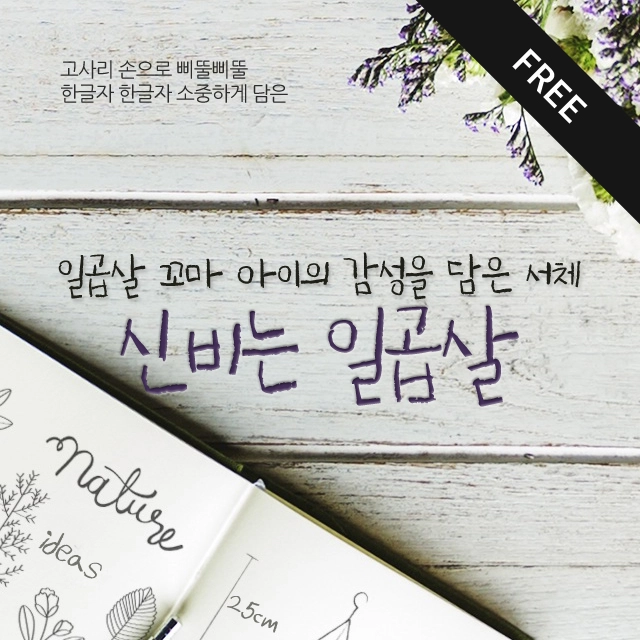
신비는 일곱살
삐뚤삐뚤 못 생겼지만, 일곱살 꼬마의 순진무구한 감성이 폴폴 풍기는 사랑스러운 폰트, 신비는 일곱살
한글 2,350자 / 영문 52자 / 약물 50자
신비는 일곱살 Regular 1종
삐뚤삐뚤 못 생겼지만, 일곱살 꼬마의 순진무구한 감성이 폴폴 풍기는 사랑스러운 폰트. <신비는 일곱살>은 이름 그대로 일곱살 꼬마 신비의 손글씨를 기초로 해서 만들어진 폰트입니다. 아빠의 갑작스러운 부탁에 작은 손가락을 꾸물럭 거리며 열심히 글씨를 써준 신비에게 심심한 감사를 표합니다. |